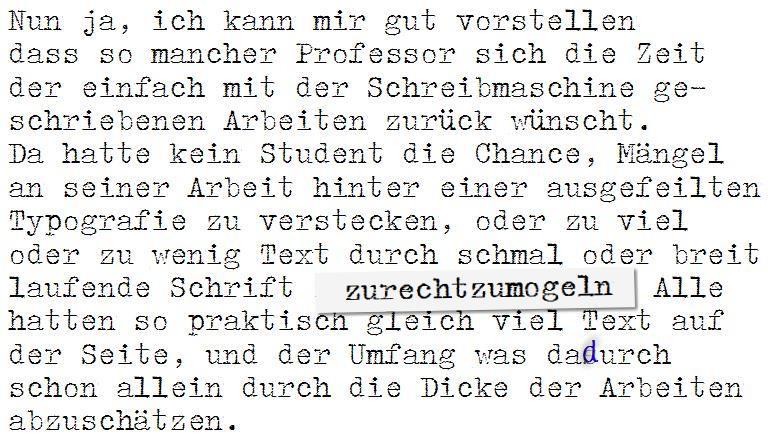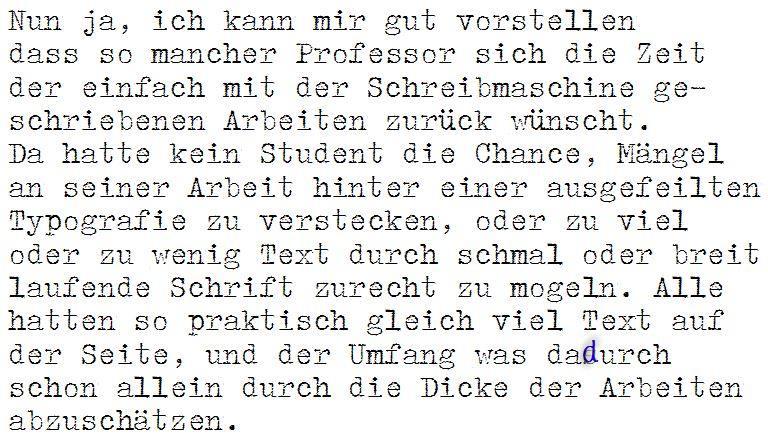
Schrift-Kombi für Projektarbeit im Bereich der Geschichtswissenschaften
Normal könntest du auf ›Bearbeiten‹ klicken und deine Tippfehler korrigieren – aber jetzt müsstest du dich wieder an die Schreibmaschine setzen und den Papierkorb füttern ... :hammer:
Bei "zurechtzumogeln" sind noch zwei Leerzeichen zuviel … :lol:
Bevor man immerzu nichts besseres weiß, als andern immer wieder und wieder das geistlose Hängen an Gewohnheiten zu unterstellen, sollte man lieber spazierengehen. Denn diese Unterstellung ist fad.
Eins noch bevor ich an die frische Luft gehe: Wenn man die Gewohnheit hat mit Gewohnheiten zu argumentieren, muss man sich nicht wundern, wenn das hinterfragt wird – auch wenn’s dir fad erscheint. Unterstellen will ich dir gar nichts, außer, dass du sicherlich sehr gute Arbeit machst und, dass du von dem was du tust sehr viel Ahnung hast. Ein Argument, warum eine Schreibmaschinenschrift für ein Manuskript besser, lesefreundlicher oder ökonomischer sein soll als die üblichen Systemschriften, hast du aber  bisher nicht genannt – außer eben deiner Gewohnheit.
Und wie in hundert anderen Antwort von Martin auch: »aber bei Tschichold steht das auch so«. Na und? Tschichold kennt und beschreibt die Möglichkeiten des heutigen Computersatzes nicht und nützt uns folglich in dieser Diskussion überhaupt nichts. Diese ewigen Autoritätsverweise sind auch »fad« und schlicht ohne jegliche Überzeugungskraft, wenn sie nicht mindestens Argumente der Autorität mitliefern.
Schnitzel hat auf eventuelle technisch bedingte Unzunglänglichkeiten und Lesbarkeitsprobleme von Schreibmaschinenschrift hingewiesen. Darüber kann man sich streiten. Gut! Aber was spricht denn wirklich dagegen? »Aber Tschichold!« ist nichts! Und dass sich das bewährt hat, müsste man erstmal zeigen. Es war üblich, als es alternativlos war. Das zeigt aber mitnichten eine Bewährung auf. Wie Schnitzel, der gerade parallel schrieb, auch feststellt: noch wurden keine Argumente genannt, sondern lediglich die eigene Konvention beschrieben.
Hab's übermalt :gimmifive:
... und das ›war‹ davor ;-)
Tippex macht so ein Manuskript aber auch nicht schöner ...
Wer einmal eines der Spätwerke Arno Schmidts, die ja zunächst als faksimilierte Typoskripte erschienen sind, zum Vergleich in der inzwischen von Forssman gesetzten Fassung vor sich hat, wird sofort den Eindruck haben, dass die Schreibmaschinenversion für den heutigen Leser eigentlich eine Zumutung darstellt. Und das kurze Textbeispiel von catfonts zeigt ja auch, dass es da mit angenehmer Lesbarkeit nicht weit her ist. Ich will dabei allerdings nicht bestreiten, dass sich solche kurzen Sachen mit der Schreibmaschine angenehm setzen lassen. Aber das geht dann eben nicht von selbst, sondern bedarf durchaus eines Mindestmaßes an – wie Martin schreibt – »typografischer Durcharbeitung«. Was soll daran also besser sein als eine Systemschrift auf heutigen PCs?
Und das kurze Textbeispiel von catfonts zeigt ja auch, dass es da mit angenehmer Lesbarkeit nicht weit her ist.
Ich finde, das beweist wenig. Zu groß, zu unsauber, zu geringer Zeilenabstand. Ich habe letztens auch eine Schreibmaschinenschrift gesucht und bin an der Colon hängengeblieben. Und einen in der Colon gesetzten mehrseitigen Text halte ich nicht für schlechter lesbar als Arial oder Times New Roman, die hier als Alternative angeboten wurden. Die digitalisierte Pica war mir bisher entgangen, aber sie bekommt eine Chance. Aber wahrscheinlich ist sie mir im Druck zu dünn.
Ich möchte nicht jede Rechnung detailtypografisch durcharbeiten, dafür fehlen mir die Zeit und die Einsicht in die Notwendigkeit und in Textprogrammen die technischen Möglichkeiten.
Das ist allerdings kein Argument. Bei der Charter müsstest du auch nicht mehr detailtypografisch durcharbeiten als bei einer Schreibmaschinenschrift. Ich finde sie jedenfalls ausgesprochen pflegeleicht.
Ein Argument, warum eine Schreibmaschinenschrift für ein Manuskript besser, lesefreundlicher oder ökonomischer sein soll als die üblichen Systemschriften, hast du aber  bisher nicht genannt – außer eben deiner Gewohnheit.
Wie Schnitzel, der gerade parallel schrieb, auch feststellt: noch wurden keine Argumente genannt, sondern lediglich die eigene Konvention beschrieben.
Das ist, was ich schrieb und was offenbar gar nicht angekommen ist:
Ich möchte nicht jede Rechnung detailtypografisch durcharbeiten, dafür fehlen mir die Zeit und die Einsicht in die Notwendigkeit und in Textprogrammen die technischen Möglichkeiten. Ich schreibe keine Briefe mit einem Satzprogramm. Meine Briefe sollen auch nicht wie Buchseiten aussehen, das würde ihren Inhalt überbewerten. Im Verlagsgeschäft arbeitet sich mit Manuskripten wie beschrieben am besten. Ich mache es also so, weil es sich bewährt hat und es keine bessere Lösung gibt bei gleichem Zeitaufwand.
Von Lesefreundlichkeit schrieb ich nichts. Meine Briefe haben keine 200 Seiten. Meine Rechnungen sind höflich formuliert, aber nicht ausufernd. Auch schrieb ich nicht von einem diffusen »besser«, sondern von einem präzisen, nämlich bezogen auf Verlagsarbeit. Was macht ein Verlag mit einem Manuskript? Ein Lektor lektoriert und redigiert. Er schreibt zwischen die Zeilen und an den Rand. Er liest langsam, er macht sich Notizen. Macht sich »besser«, wenn die Zeile 60 Anschläge hat und die Seite nur 30 Zeilen als mit einer Vorgabe von einem Textprogramm wie WORD. Und der richtige Satz kommt anschließend an die Reihe, denn es wäre Verschwendung, wenn man jede Textfassung aufs neue typografisch durcharbeitete.
Man kann auch ganz einfach in der »Detailtypografie« nachschlagen, wenn man diese Argumente und weitere noch viel gründlicher nachlesen und prüfen möchte.
Wir schlagen jetzt mal alle unseren Forssmann auf und suchen uns die Argumente für Martins Thesen raus ...